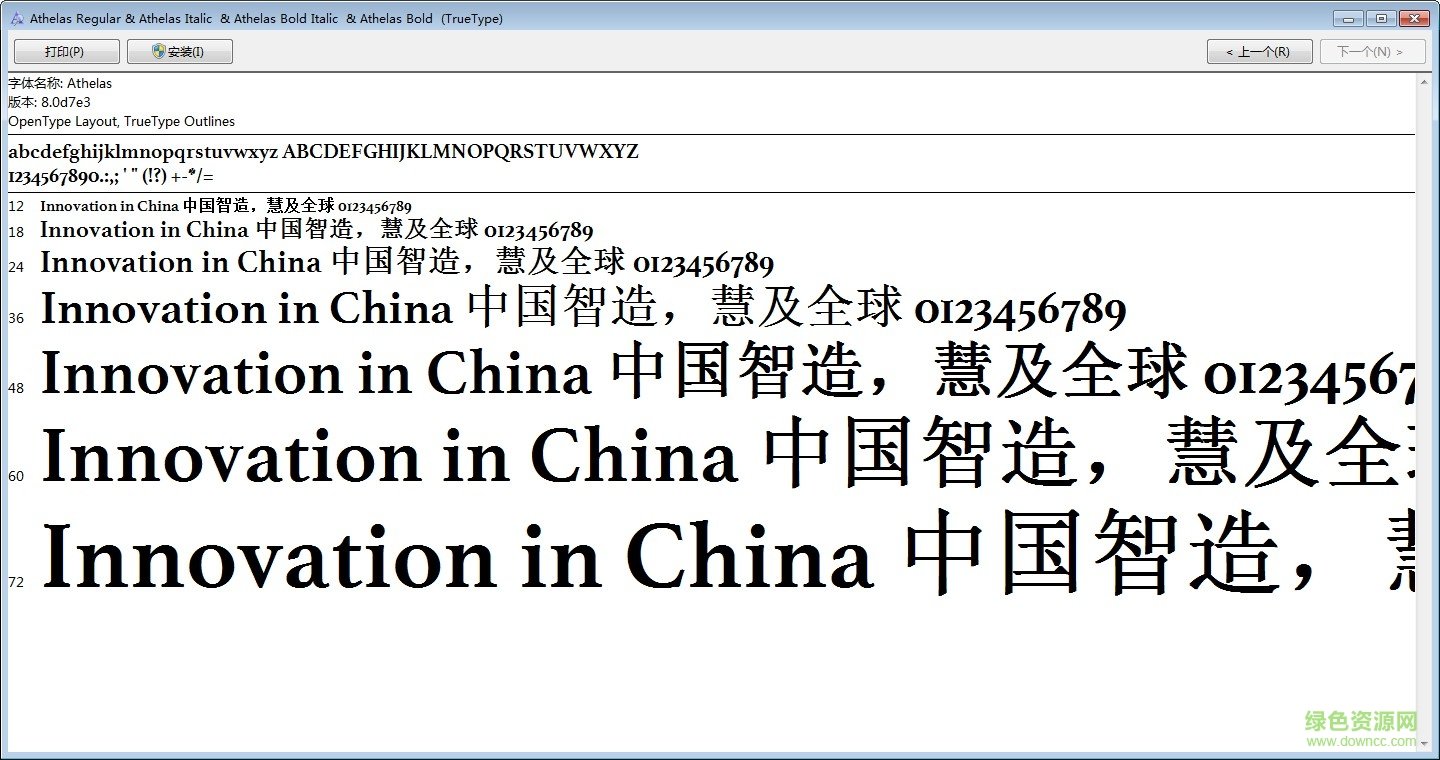
athelas bold 字體是一款經(jīng)典的英文字體,字體點(diǎn)畫呼應(yīng),結(jié)構(gòu)輕巧,線條雖粗又不失秀美,辨識(shí)度高,有需要者歡迎在綠色資源網(wǎng)下載!
字體造型規(guī)整,富于力度,給人以簡(jiǎn)潔爽朗的現(xiàn)代感,有較強(qiáng)的視覺沖擊力,這種個(gè)性的字體,適合于機(jī)械科技等主題。